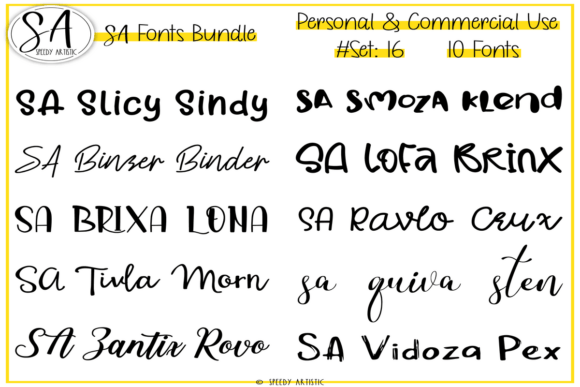
Script and Handwritten Bundle 16
Nếu bạn đang tìm kiếm các tài nguyên chất lượng cao như Script and Handwritten Bundle 16, gói cao cấp này là một lựa chọn tuyệt vời cho các dự án sáng tạo của bạn.
Được chế tác với độ chính xác cao, Script and Handwritten Bundle 16 cung cấp các vector sạch, kiểu chữ mượt mà và giấy phép thương mại để bạn yên tâm.